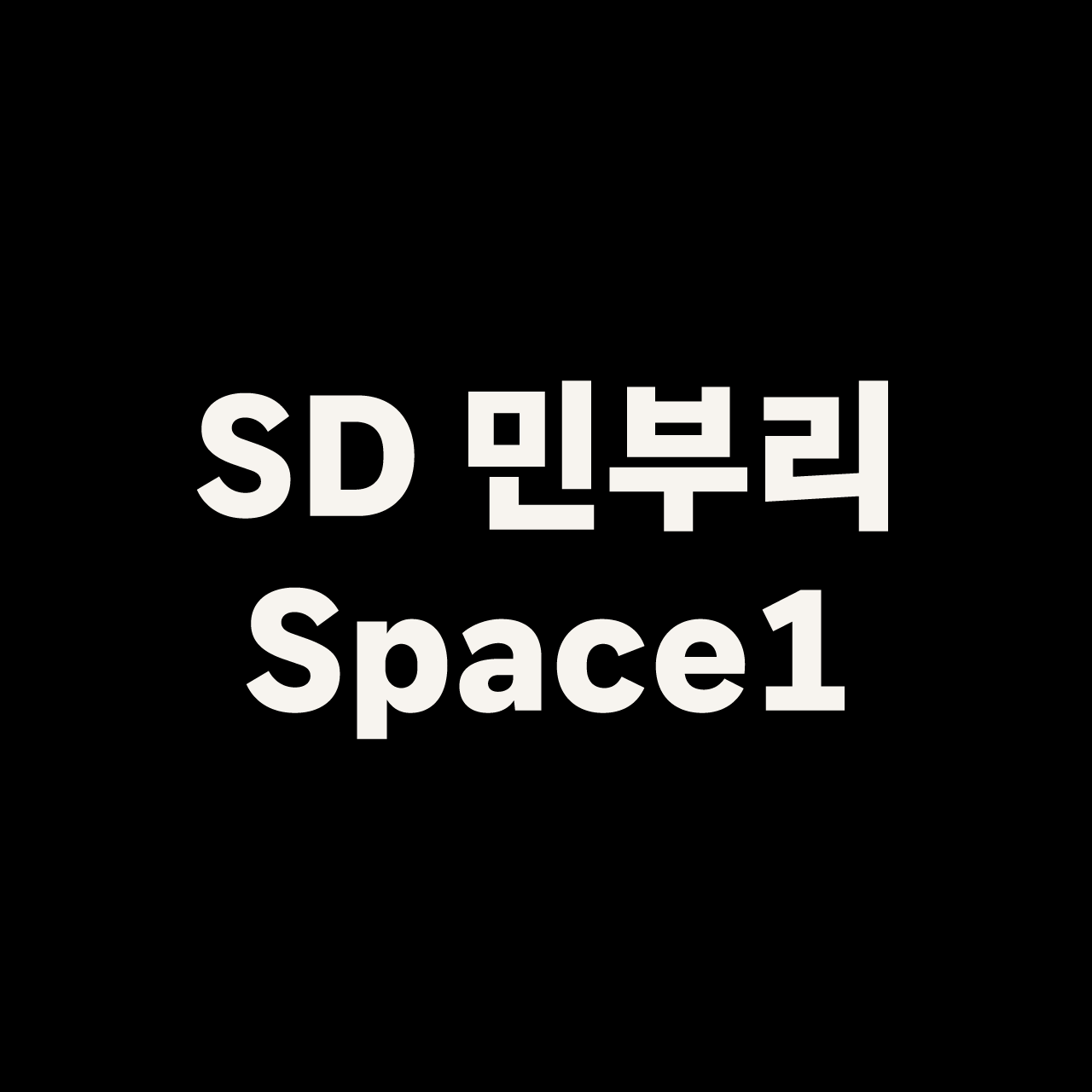
SD 민부리 Space1
「SD 민부리」는 변화하는 사용 환경에 맞춰 새롭게 디자인된 본문용 민부리 폰트입니다. 직선적으로 디자인된 사선획과 스퀘어리시한 속공간, 연결된 획 등 기하학적인 캐릭터로 인해 간결하고 깔끔한 인상이 특징적입니다.
또한 다양한 Weight와 Space(속공간)으로 제작되어 본문용부터 제목용까지 여러 용도에 따라 선택해 사용하실 수 있습니다. 전체 패밀리는 속공간의 크기에 따라 총 6가지로 구성되어 있으며 각각 100-900까지 9개의 웨이트를 포함합니다.
그 중 Space1은 가장 작은 속공간을 가지고 있는 패밀리입니다. 본문용이지만 조밀한 자소가 주는 약간의 서정적인 인상이 특징적입니다.
「SD 민부리」는 UI에서의 쓰임을 고려하여 다양한 아이콘 형태의 글립과 임의 합자, 스타일리스틱 세트 등 OpenType 기능을 제공합니다. 또한 다국어 문자 세트 구비를 목표로 하여 현재는 라틴 확장을 포함하며, 추후 CJ가 업데이트 될 예정입니다.